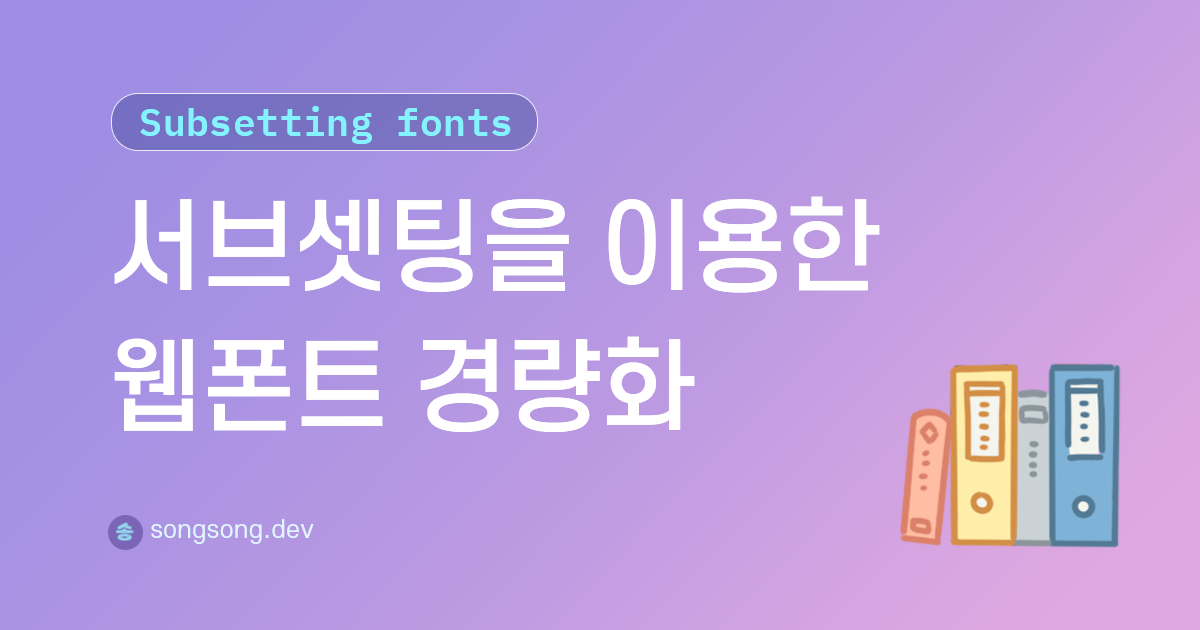
서브셋 폰트란?
웹폰트를 경량화할 때 보통 원하는 문자 글리프만 남기고 나머지 데이터는 삭제하는 방법을 이용한다. 이걸 서브셋폰트, 폰트 서브셋팅이라고 부른다. 필요한 글자만 남기고 나머지는 다 삭제하기 때문에 만약 페이지에서 이 삭제된 글자를 출력하려 하면 제대로 출력할 수 없다.
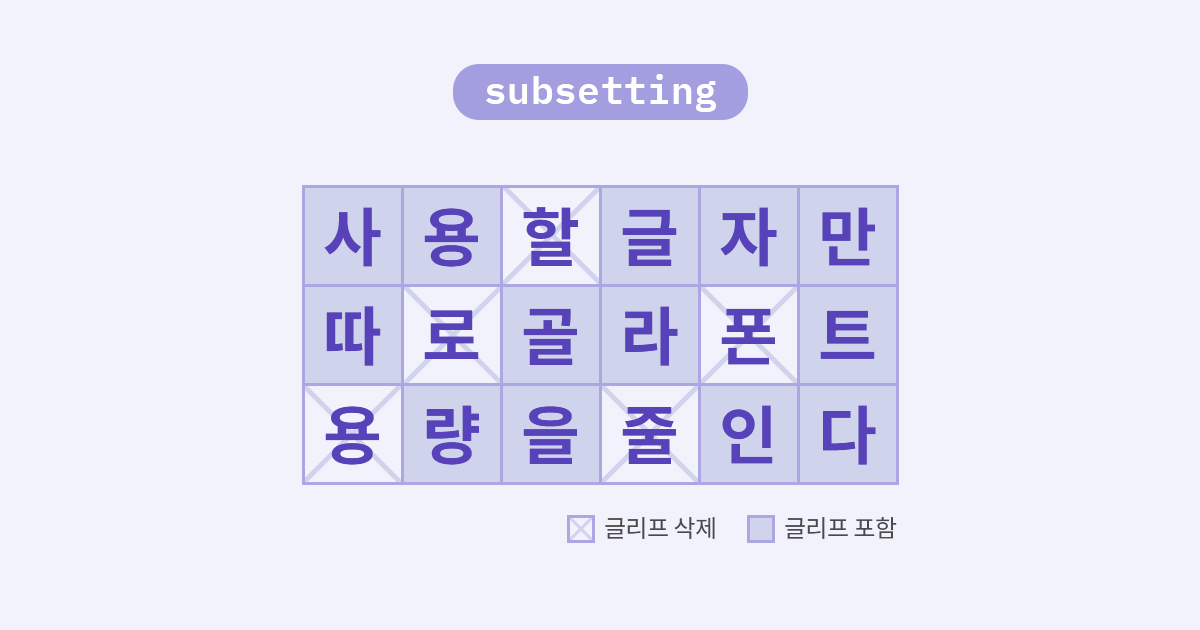
보통 인터넷 상에서 변환된 웹폰트 파일을 다운로드 하여 바로 사용하는 경우 가끔 특수문자나 몇몇개의 글자가 보이지 않는 경우가 가끔 있다. 이럴 때에는 원본 폰트에서 서브셋 폰트를 직접 만들어 해결하면 된다.
서브셋팅으로 웹폰트 경량화 하기
변환 전 확인 사항
1. 이용자가 서비스에서 직접 입력하는 것인지 확인해본다.
이용자가 직접 입력하는 서비스라면 글자를 작성하면서 자주 쓰이지 않는 글자를 입력하게 된다. 특히 종성이 ㄱ,ㄴ,ㄹ, ㅂ 이고 다음 글자 초성이 ㄱ,ㅁ,ㅅ,ㅈ,ㅎ로 겹받침이 생길 때가 특히 많다. 서브셋 리스트에 없는 글자를 입력했을 때, 해당 글자에는 해당 웹폰트가 적용되지 않으므로 주의하여 사용 한다.
2. 원본 폰트 파일에서 해당 글리프를 지원하는지 확인해본다.
한글 폰트에서 자주 한글 문자 글리프를 제외하고 자주 사용하지 않는 특수문자 등은 아예 글리프를 제작하지 않는 폰트들이 가끔 있다. 애초에 만든 적이 없는 글리프를 새로 만들어낼 순 없으므로, 그럴 땐 해당 문자를 다른 폰트로 대체 해야 하는 것이 더 바람직하다.
서브셋 리스트
어떤 글자를 남기고 어떤 글자를 버리는 것이 좋을까? 자주 사용하는 것은 포함하고, 거의 사용하지 않는 글자를 삭제하는 게 바람직할 것이다. 일반적으로 통용되는 리스트는 아래와 같다.
한글 자모, 알파벳, 숫자, 구두점을 기본으로 한국 산업 규격으로 지정된 한국어 문자 집합 KS X 1001 표준과 아래 논문에서 제시된 글자 224자를 추가해 사용한다.
서브셋 웹폰트 변환 하기
웹사이트를 이용한 변환 서비스가 이미 존재한다. 온라인 상에서 서브셋 제작 및 ttf, woff, woff2, svg, eot 웹폰트 변환 모두 지원한다. 따로 프로그램을 사용하거나 서브셋을 만든 후 웹폰트 변환을 따로 해야하는 식의 번거로운 과정이 필요 없어 편리하다.
sebsets는 미리 지정해둔 서브셋 목록이다. 한글 서브셋은 따로 없으므로 characters에 위의 리스트를 입력하면 된다. 원본 otf 혹은 ttf 파일을 업로드 하면 웹폰트 형식으로 변환 및 다운로드 가능하다.
실제 적용 사례
스포카 한 산스 네오
스포카 한 산스는 한글 글리프는 NotoSans에서 가져오고 숫자 글리프는 Lato 폰트를 참고하여 어울리게 개작한 폰트이다. 숫자가 많이 쓰이는 서비스에서 사용하기 위해 만들어진 폰트로 국문, 특수문자, 숫자 등의 밸런스 및 만듦새가 좋아 많이 쓰인다.
문제 확인
홈페이지에서 스포카 한 산스 네오의 원본 폰트(오리지널) 및 경량화 폰트(서브셋)도 같이 제공해주고 있다. 제작하는 홈페이지에서 스포카 한 산스 네오에서 기본으로 제공하는 서브셋 폰트를 사용했을 때 특수문자가 제대로 출력되지 않았다.
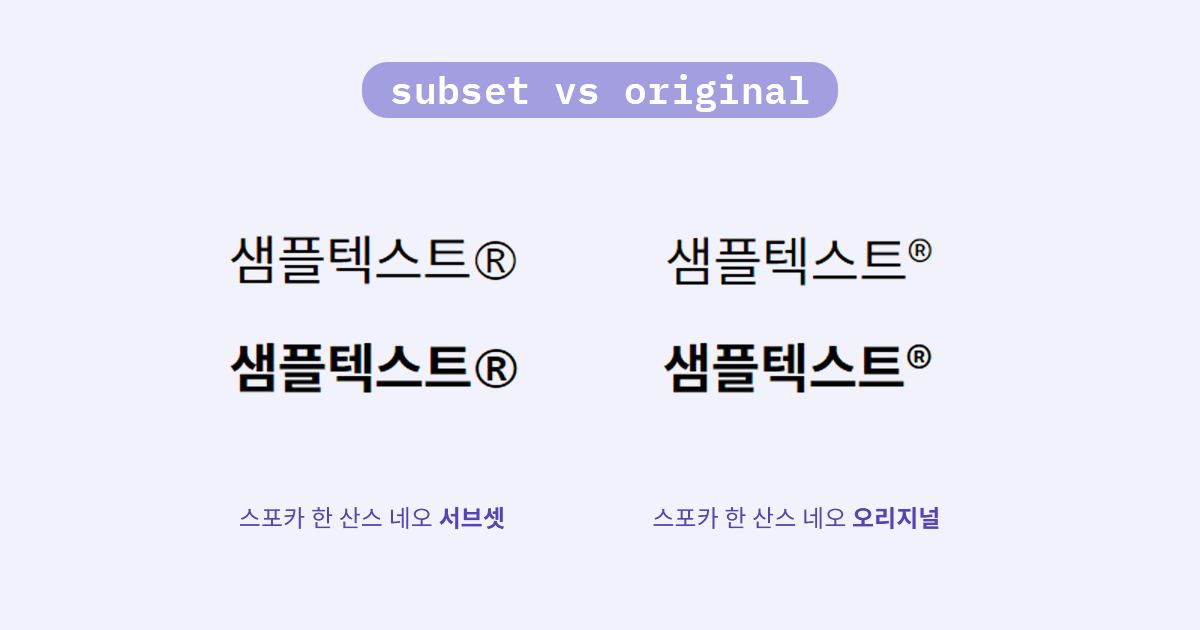
원본 디자인은 우측처럼 R 글자가 위첨자로 들어가야 한다. 형태도 다르고 베이스 라인도 맞지 않다.
서브셋팅으로 폰트 파일 교체
1. 먼저 오리지널 폰트 파일에서 제대로 출력되는지 확인한다.
디자인 파일 상에서는 제대로 보이는데, html로 작성했을 때에만(서브셋 폰트를 사용했을 때) 이상하게 나타난다. 오리지널 폰트 파일에는 위 문자 모양 데이터가 있으나, 스포카에서 제공하는 서브셋 폰트에는 글자가 빠져 있는 탓이다. 이럴 때 해당 글리프를 포함하여 다시 서브셋을 만들어주면 된다.
2. 해당 글자가 위의 서브셋 리스트에 있는지 확인한다.
3. 오리지널 파일을 이용하여 위의 사이트에서 서브셋 폰트를 제작한다.
4. 기존 폰트 파일을 새로 제작한 웹폰트 파일로 바꾸면 제대로 출력된다.